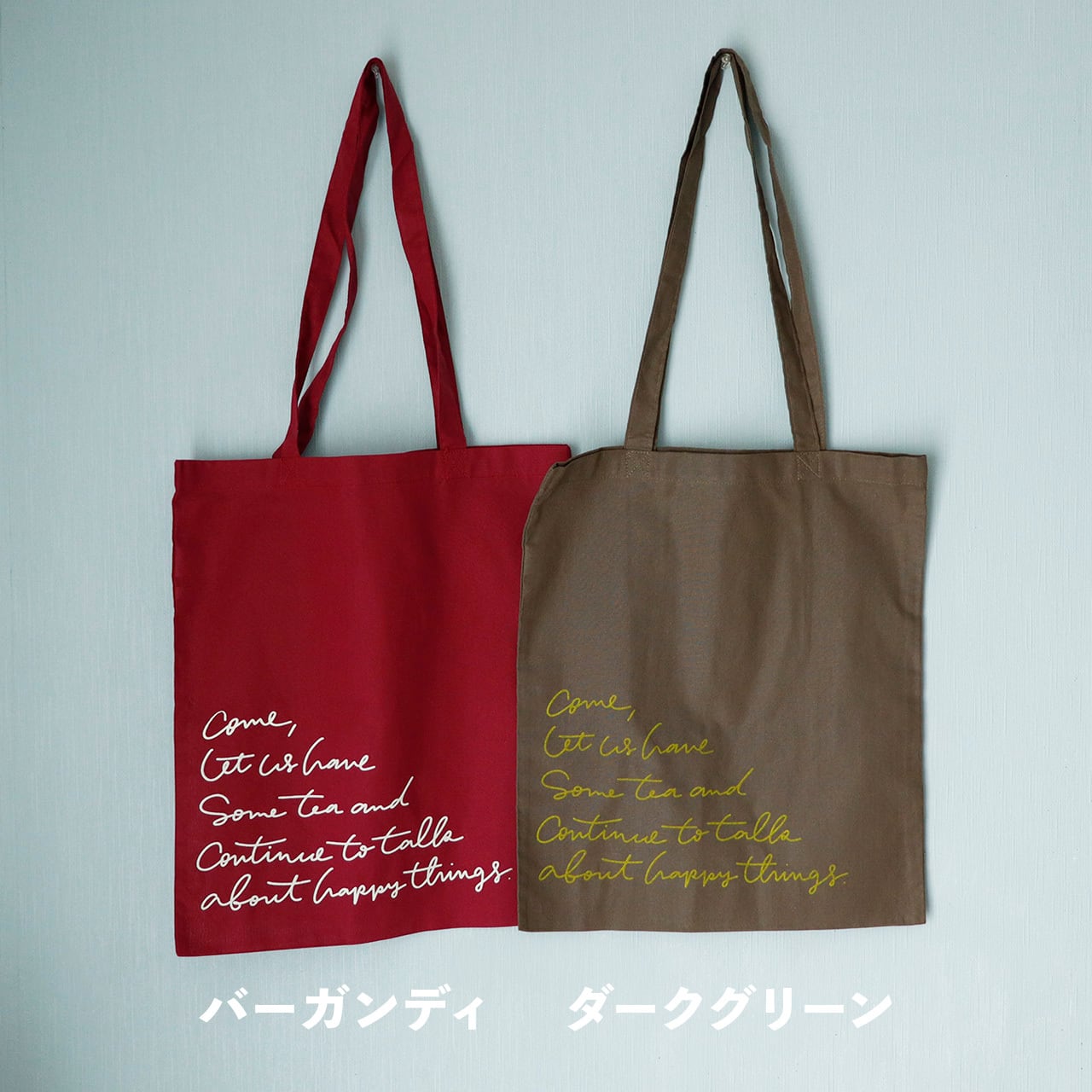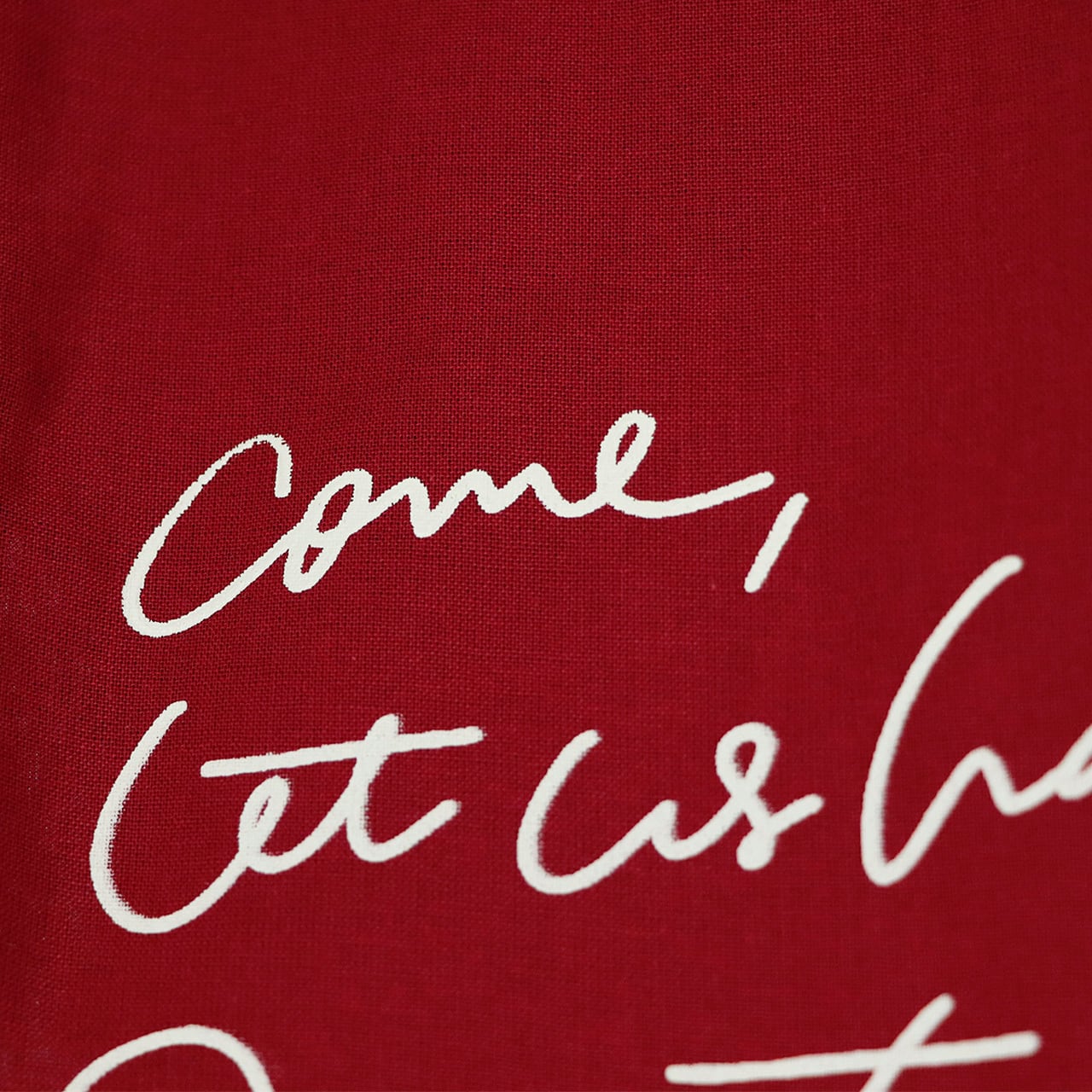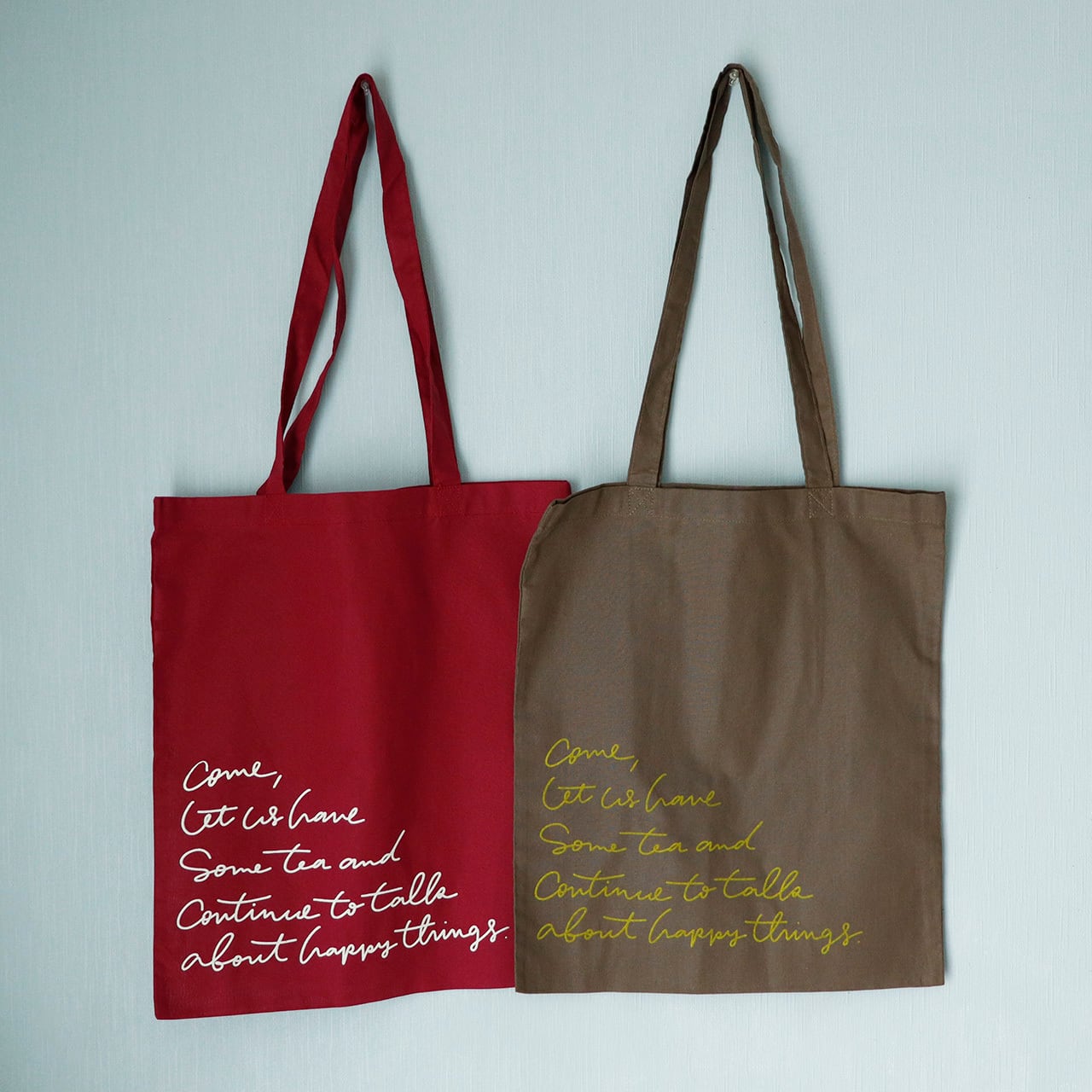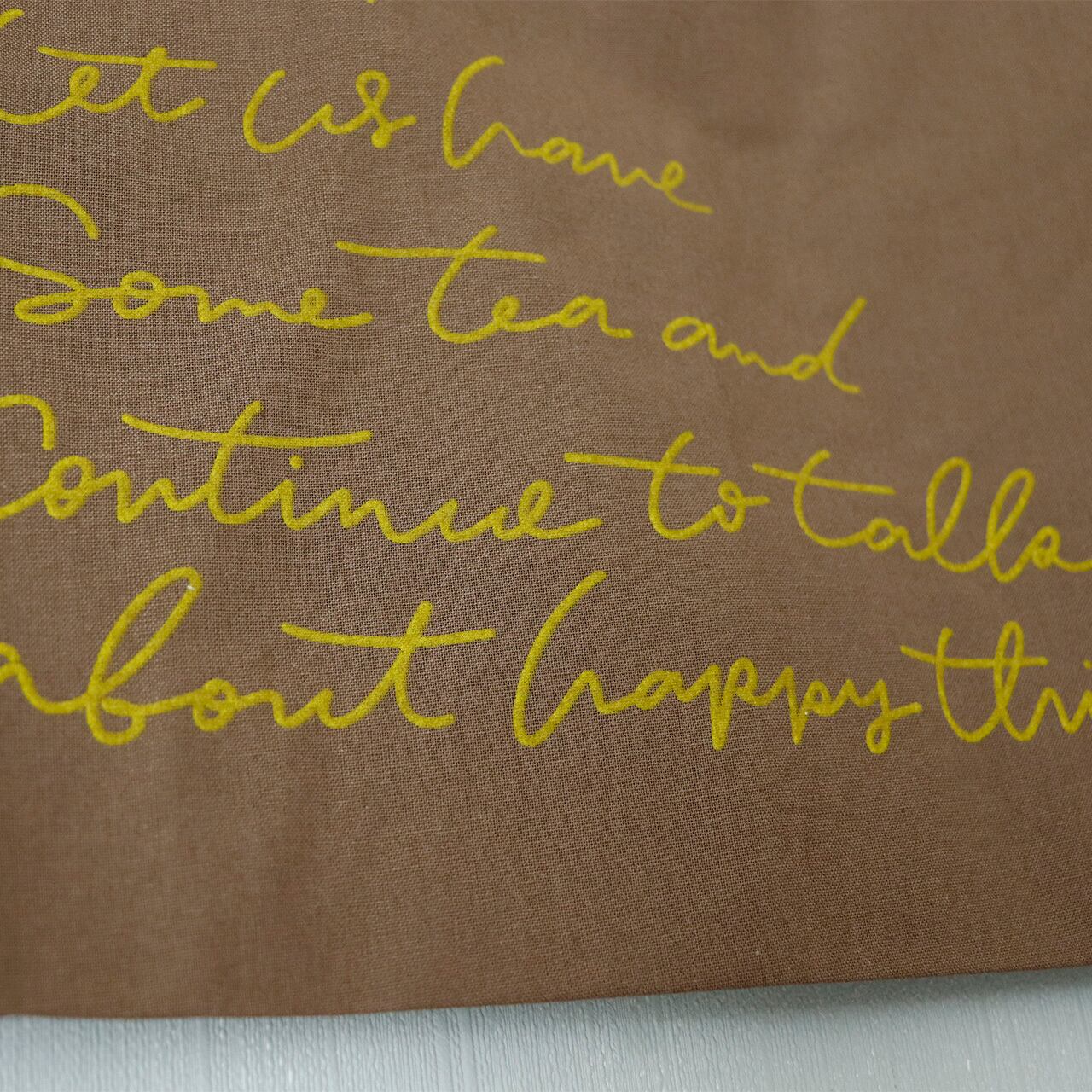
TEAトートバッグ(バーガンディ/ダークグリーン)
Come, let us have some tea and continue to talk about happy things
さあ、お茶を飲んで幸せなことについて話し続けよう
バーガンディは紅茶にミルクを、ダークグリーンは緑茶とレモン(なかなかいける)をイメージしました。
くるくる筆記体で混ぜてます◎
一点ずつシルクスクリーンで手刷りしています(私が!!!)
そのため若干のかすれなどがありますが、手刷りの「味」として楽しんでもらえると嬉しいです。